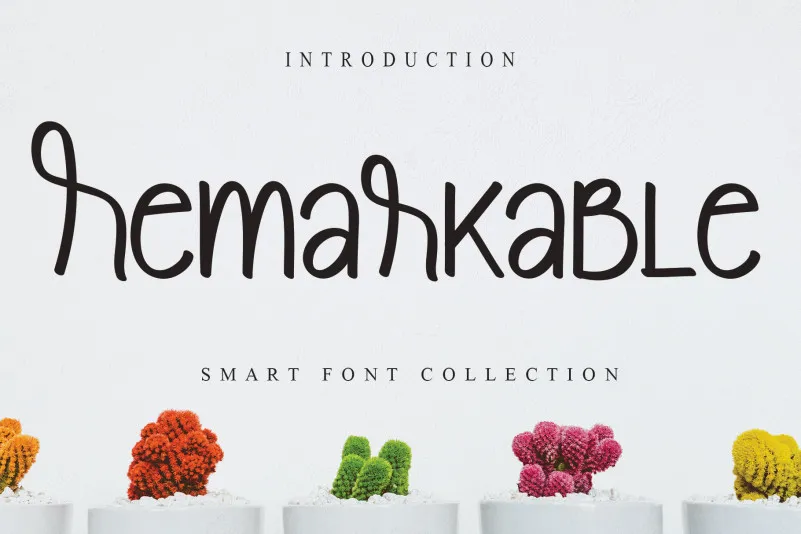
A fonte Remarkable Display Font é uma escolha inteligente para quem busca uma experiência visual notável em seus projetos visuais. Seu design criativo e arrojado permite que você deixe sua marca com um estilo único, seja num site moderno e dinâmico ou em um infográfico cheio de detalhes. Remarkable Display Font foi pensada para se destacar no meio das fontes padrão, trazendo uma paleta vibrante de cores e formas orgânicas que criam impactos visuais marcantes. Suas linhas finas, sua tipografia extrema e suas proporções arredondadas são projetadas para serem utilizadas em aplicações onde você deseja chamar a atenção do público. O designer creativeletter soube capturar o espírito de uma fonte display ao criar um conjunto de caracteres que não se prende à realidade, mas sim expande seus limites. Essa característica inovadora faz com que Remarkable Display Font seja ideal para aplicações que exigem uma presença forte em seu campo ou indústria. Com a Remarkable Display Font, você terá a oportunidade de criar algo realmente único e impactante, deixando um grande sinal no meio das montanhas. Essa fonte é a escolha perfeita para designers buscando expressar sua criatividade em nível máximo.